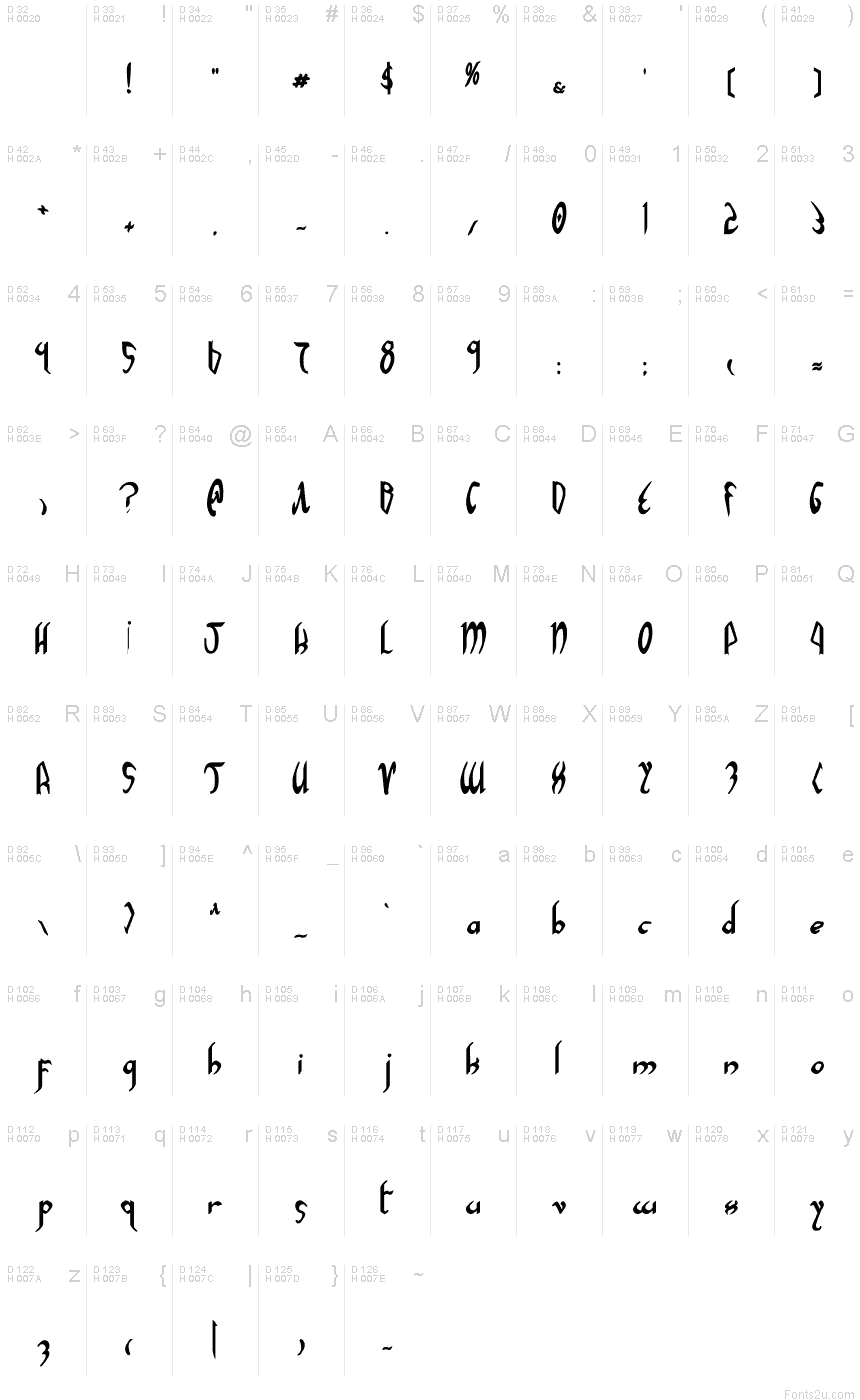
Podgląd czcionki Xaphan Bold
Xaphan Bold od Iconian Fonts to darmowy gotycki krój pisma o ostrym, średniowiecznym charakterze. Jego litery łączą dramatyzm czcionek łamanych (blackletter) z nieco bardziej nowoczesną rytmiką, przeplatając ostrza i haczykowate zakończenia zaokrąglonymi formami, dzięki czemu napis jest dynamiczny, a nie przytłaczający.
Ten darmowy font idealnie sprawdza się na okładkach fantasy, metalowych ulotkach, ekranach tytułowych gier, nagłówkach plakatów i krótkich logotypach, wszędzie tam, gdzie potrzebny jest mroczny, historyczny klimat. Pasuje również do inicjałów i nagłówków rozdziałów, ponieważ wysokie, strzeliste kształty oraz rozdzielone, zawinięte linie nadają nawet kilku literom silny, heraldyczny wyraz.